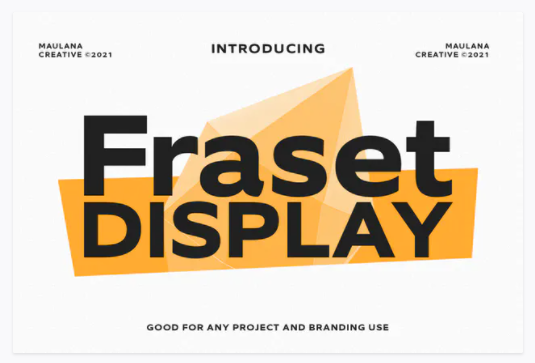
Elements.Envato Fraset Sans Serif Display Font 2021
[Elements.Envato] Fraset Sans Serif Display Font (2021)
Fraset Display - это современный шрифт без засечек. С жирным начертанием, веселым характером и некоторыми лигатурами. Это придаст вам дополнительную креативность. Шрифт Fraset Display поддерживает более 100+ языков. Этот шрифт хорошо подходит для дизайна логотипов, социальных сетей, названий фильмов, книг, короткого текста, даже длинных букв, а также для вторичного шрифта со скриптом или фирменным шрифтом. Сделайте потрясающую работу с помощью шрифта Fraset Display.